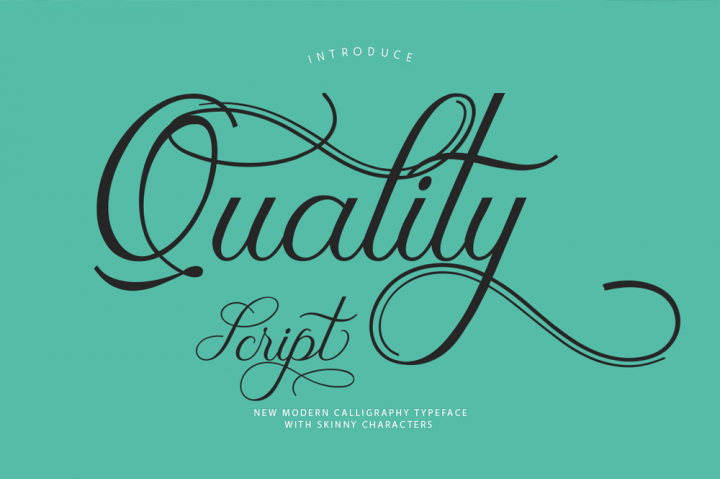
Quality Script Font – Fonte Grátis
Quality Script Font
A “Quality Script” é uma fonte script moderna e fresca, criada para capturar a essência dos designs digitais contemporâneos enquanto preservando o encanto das tipografias manuais. Suas características decorativas e linhas onduladas oferecem um toque único, adequado para diversas aplicações como cartões de convite, cartelas de boletins, cards de negócios, frases motivacionais e até mesmo outdoors. Esta fonte é perfeita para aqueles que buscam um equilíbrio entre a elegância clássica da tipografia manuscrita e a simplicidade moderna da tipografia digital. Composta com precisão, ela se adapta a vários formatos e tamanhos de texto, permitindo uma experiência visual única em qualquer projeto gráfico que você possa imaginar.